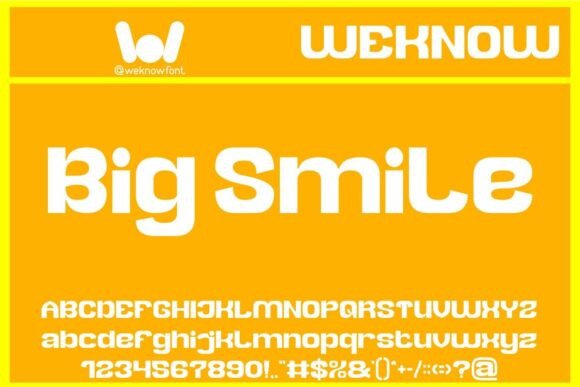
Big Smile
Trouver les bons éléments de conception peut être un défi, mais Big Smile propose une collection exceptionnelle qui rehausse instantanément votre travail.
Que vous créiez des produits POD (impression à la demande), des invitations de mariage ou des visuels pour les réseaux sociaux, Big Smile est un choix idéal.